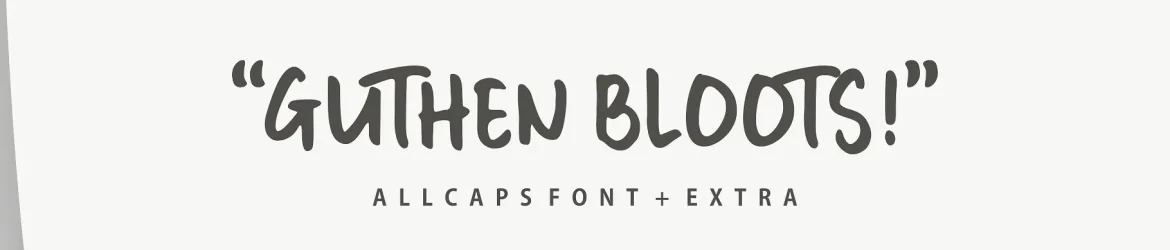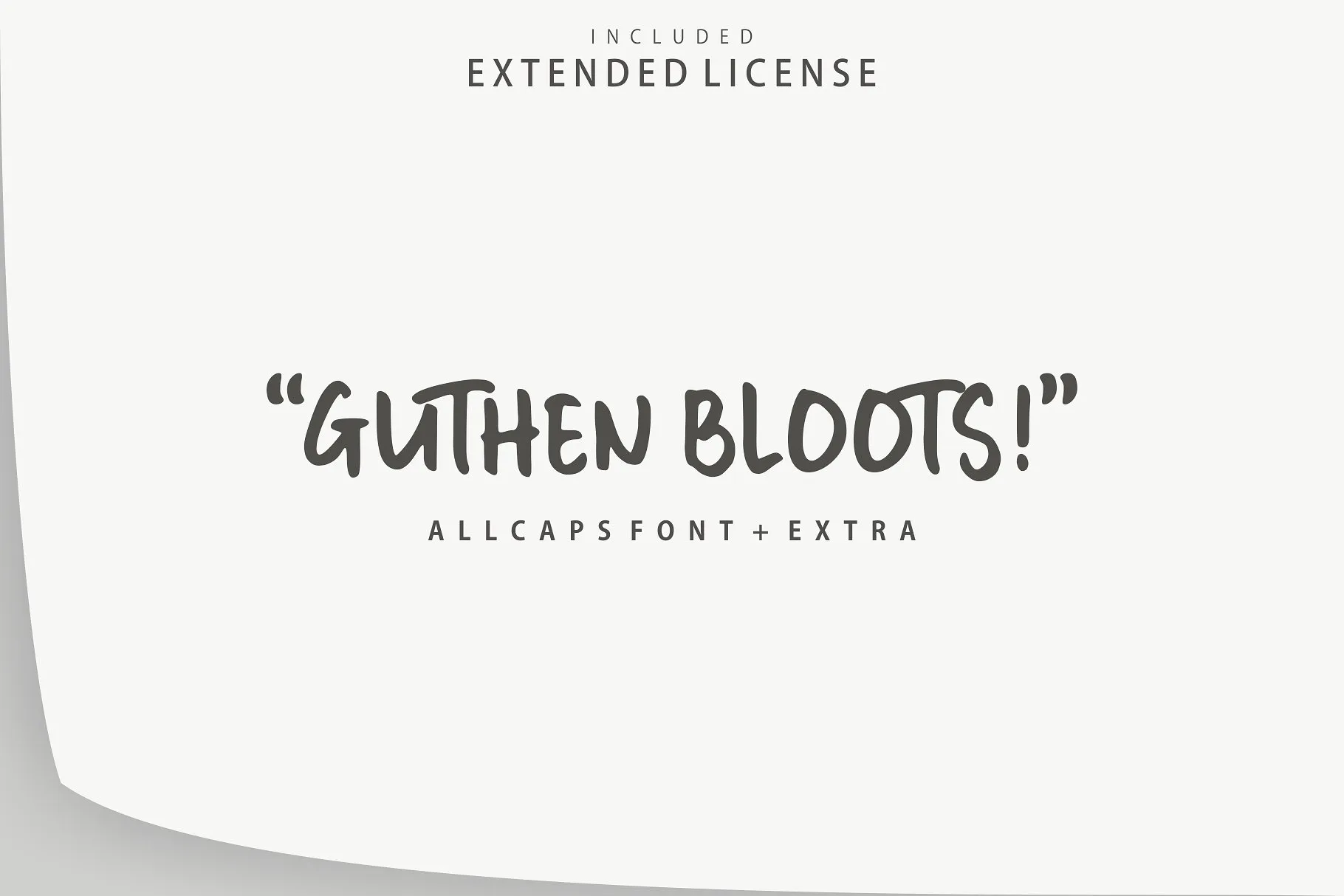
Guthen Bloots Allcaps Font – Fonte Grátis
Guthen Bloots Allcaps Font
Olá! Estou procurando por uma fonte para seu próximo projeto? Este Guthen Bloots Font é perfeito para você. Introduzimos essa elegante e única solução criada pelo designer zziplex, que se baseia no trabalho inspirador de Azetype. Guthen Bloots foi projetado com um design meticuloso em cada caractere, garantindo uma combinação perfeita dos símbolos. Suas formas distintas não apenas fazem o texto destacar em seu projeto, mas também proporcionam uma proximidade dinâmica e agradável. Essa fonte está disponível para qualquer necessidade de seus projetos. Ela pode ser usada instantaneamente em qualquer trabalho que você estiver desenvolvendo. Em suas apresentações, você poderá apreciar como o Guthen Bloots se destaca com seu charme elegante e sofisticado. Além disso, veja na foto da apresentação acima: o Guthen Bloots aparece impecável em projetos de design. Sem dúvida, vale a pena experimentar.